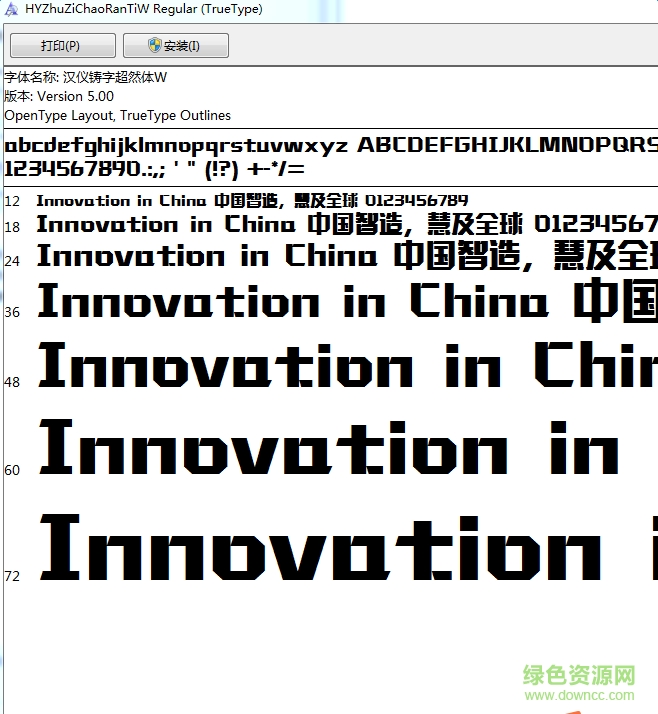
漢儀鑄字超然體是一款漢儀類(lèi)非主流風(fēng)格字體軟件,超然體筆畫(huà)看似雜亂文章,卻透露出非凡的可愛(ài)氣息,整體效果十分萌怪,還有更多類(lèi)似好看字體歡迎來(lái)綠色資源網(wǎng)下載體驗(yàn)!
該字體粗細(xì)相間,字體筆畫(huà)隨意,以黑粗體描繪點(diǎn)筆畫(huà),非常的文雅脫俗,整體效果十分時(shí)尚好看,感興趣的朋友歡迎免費(fèi)下載使用!